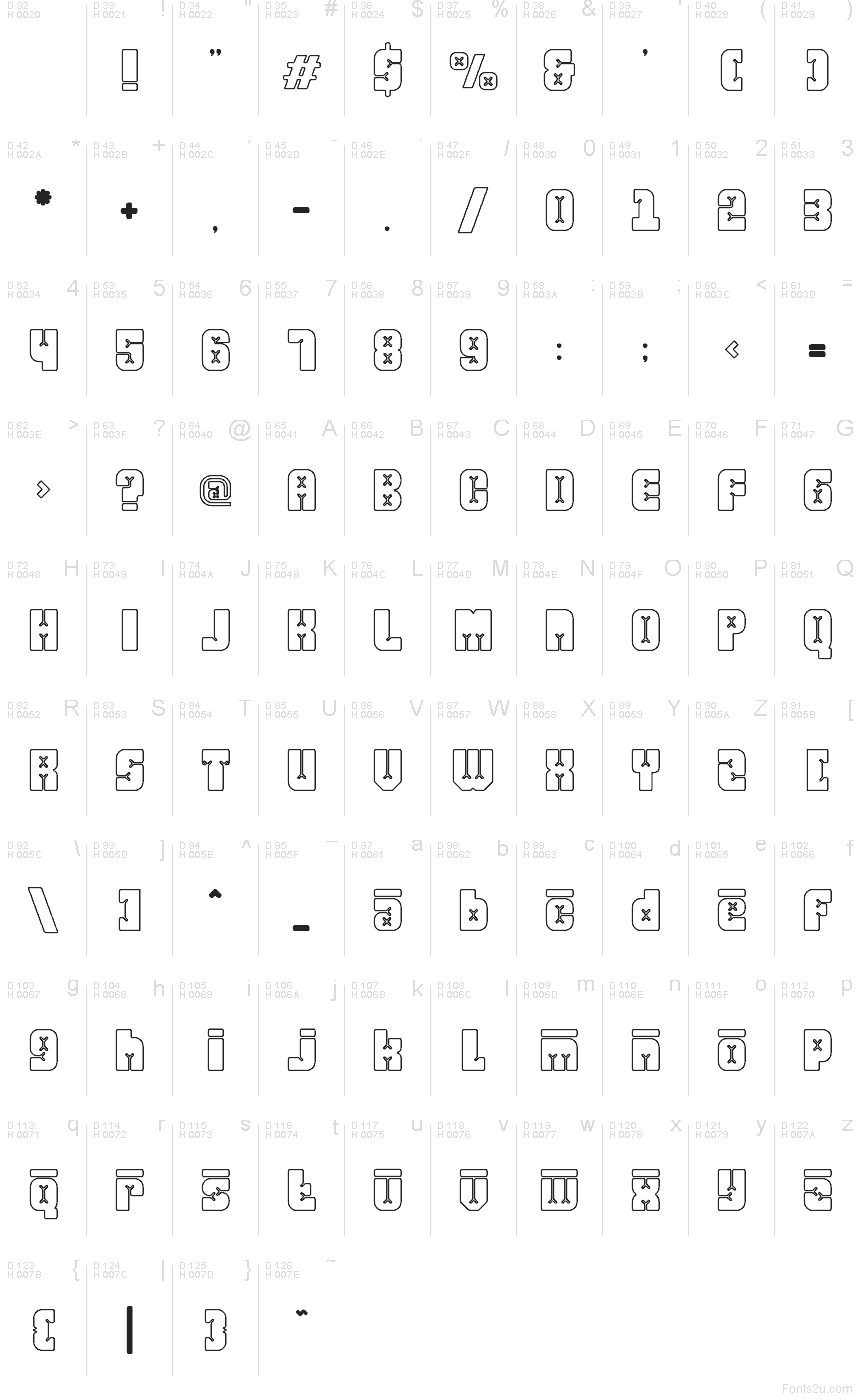
Friez Four od Putracetol Studio je bezplatné, groovym stylem inspirované písmo typu display s obrysovým designem. Jeho tvary působí jako nateklé, téměř nafouklé, a jsou uspořádány do kompaktního a stabilního rytmu. Široké křivky a vnitřní linie dodávají písmenům plakátovou váhu, zatímco drobné detaily ve větvících se částech mu dodávají charakter, díky němuž nepůsobí jen jako obyčejný „bubble“ styl.
Kombinace masivní siluety a dekorativních vnitřních prvků se skvěle hodí pro hudební letáky, branding v retro stylu 70. let, obaly, příspěvky na sociální sítě a krátké nadpisy ve stylu loga. Friez Four může také tvořit základ pro názvy akcí nebo grafiku na merch, kde zaoblené bloky zajišťují okamžitý vizuální dopad a obrysová konstrukce ponechává prostor pro vrstvení barev.